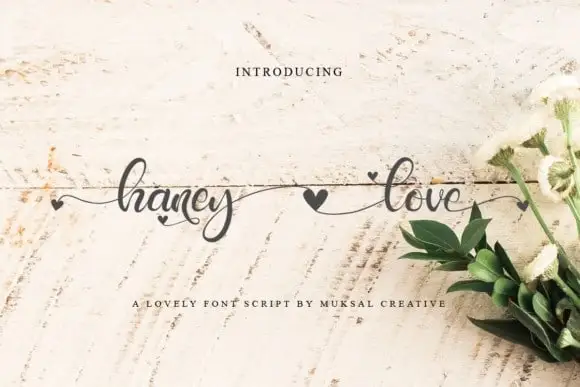
Haney Love Calligraphy Font – Download Grátis
A Haney Love Calligraphy Font é uma fonte de calligrafia moderna e natural, projetada para tornar qualquer design mais sofisticado e encantador. Fabricada pela Muksalmina através de 99designs, esta fonte vem em estilo moderno e único, com um toque agradavelmente natural na escrita. Suas formas são elegantes e diferentes do que normalmente vemos em outras fontes de calligrafia, o que torna essa fonte perfeita para aplicar ao seu trabalho no casamento, quando você deseja dar uma sensação delicada e especial a seus convites de casamento ou cartões de agradecimento. Ela também é ideal para criar cartas de saudações, rótulos empresariais e até mesmo logotipos de negócios, sempre fornecendo um toque autêntico e amigável que faz sua peça de design realmente chamativa e memorável. Com uma sensibilidade incrível em cada letra, a Haney Love Calligraphy Font é a fonte perfeita para aqueles que desejam tornar seus designs mais expressivos e únicos.